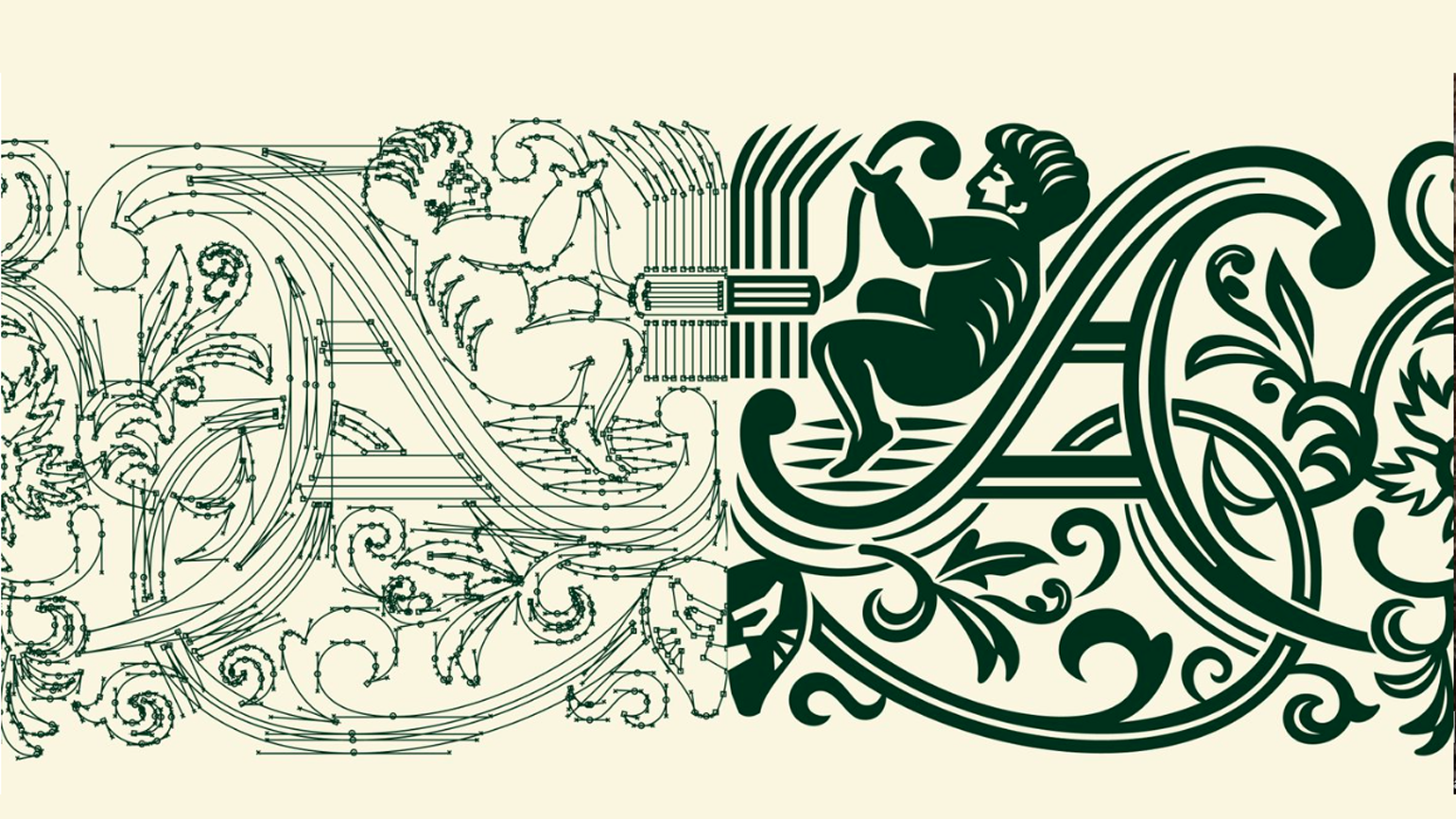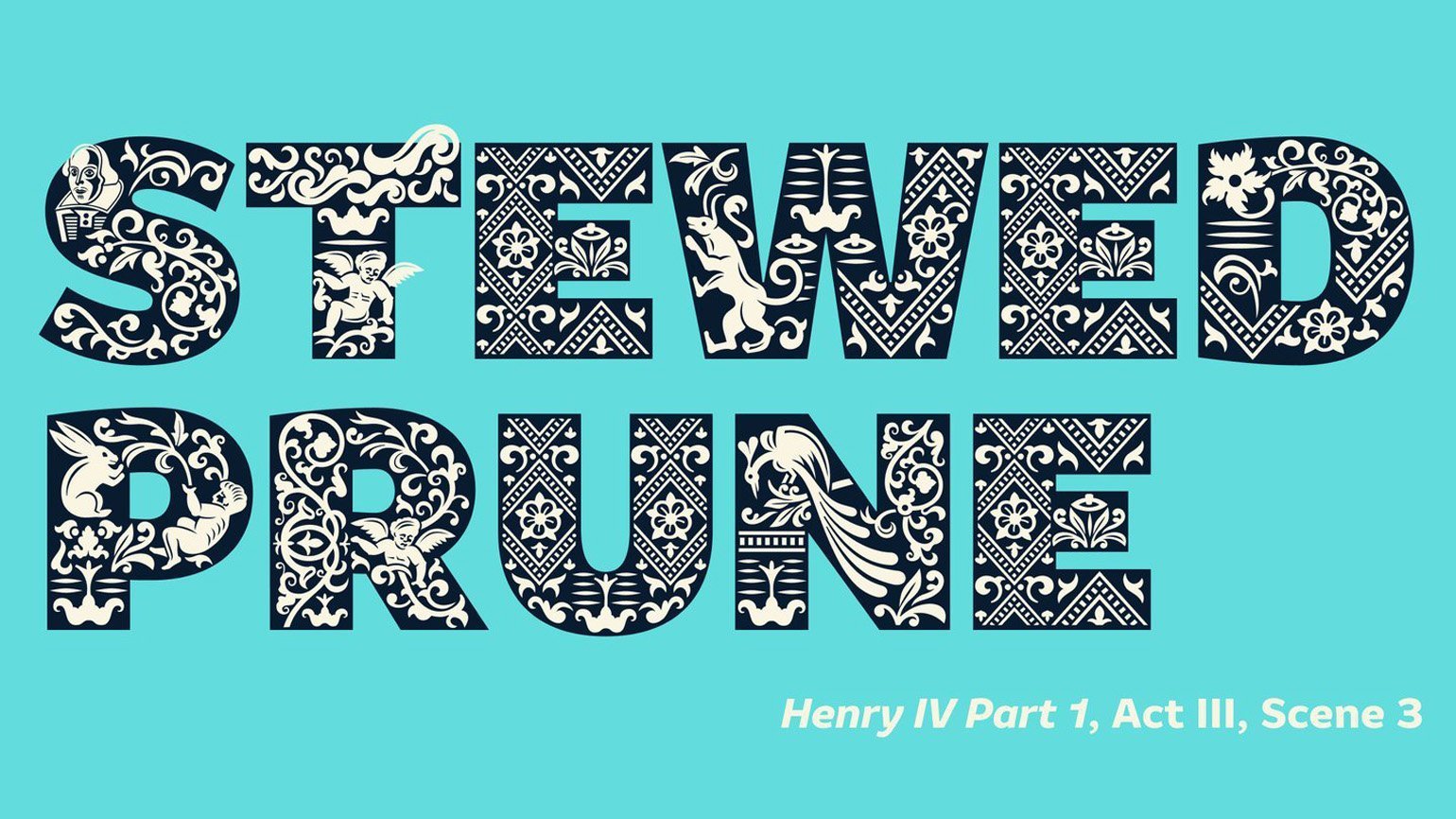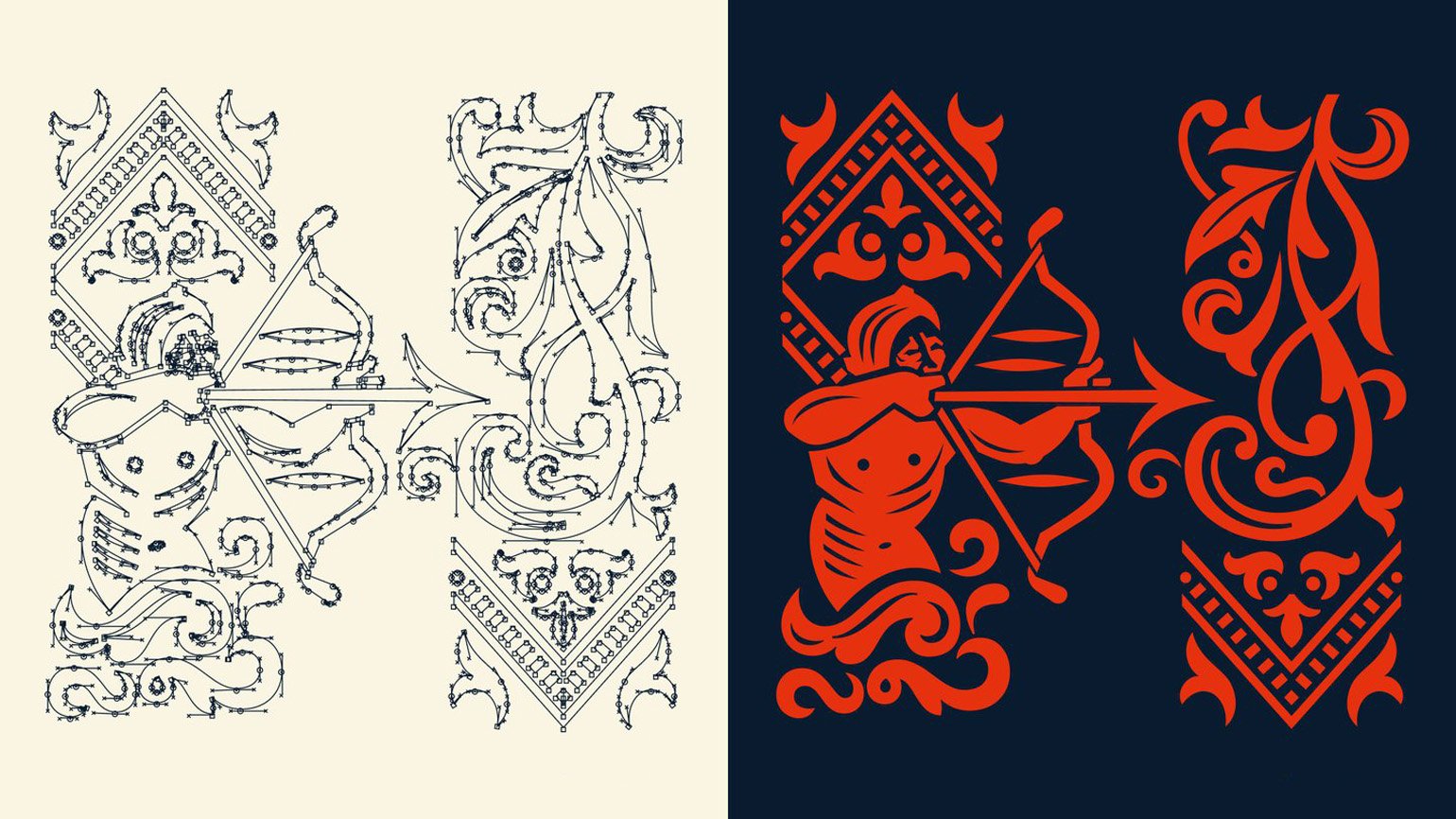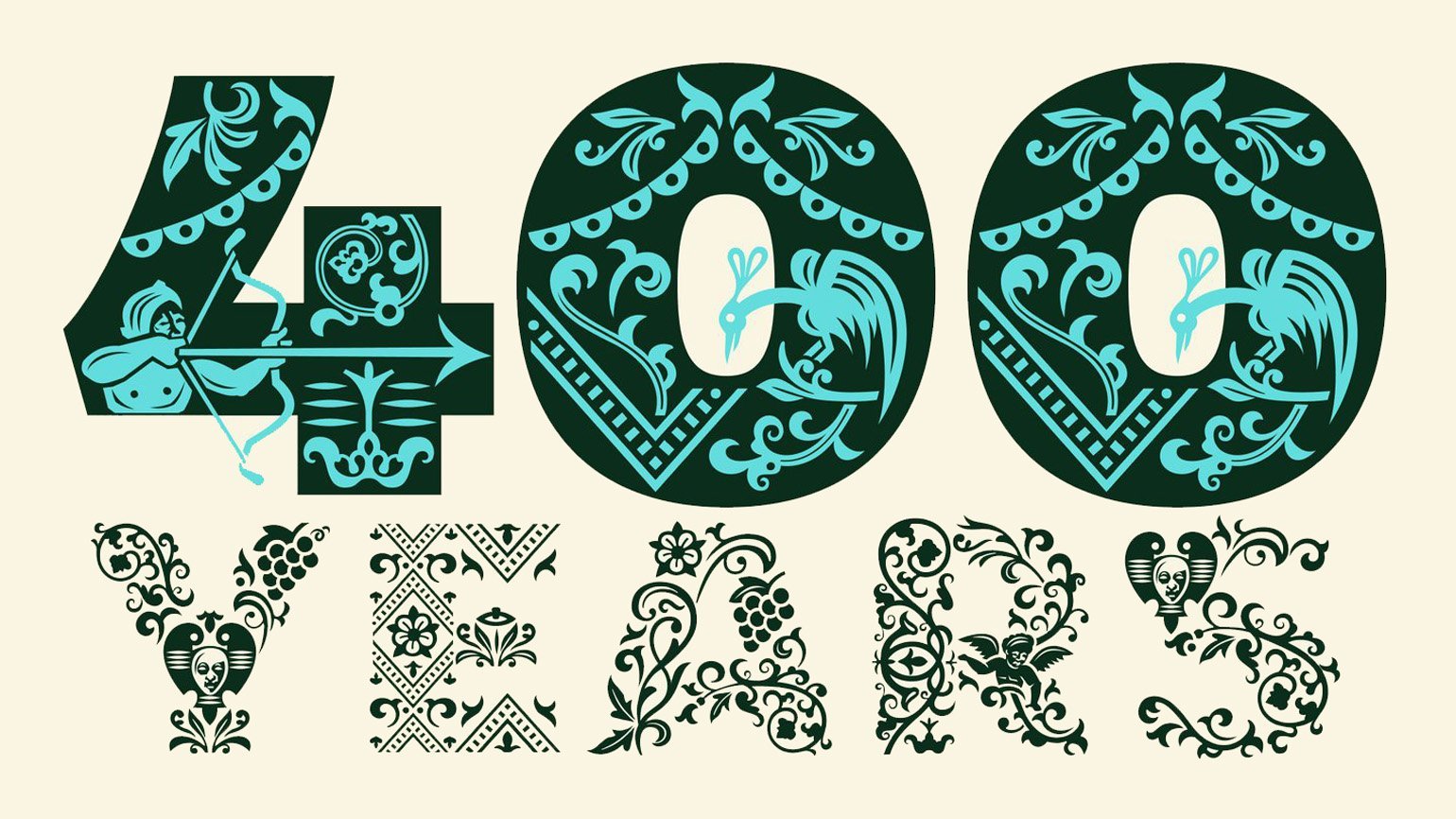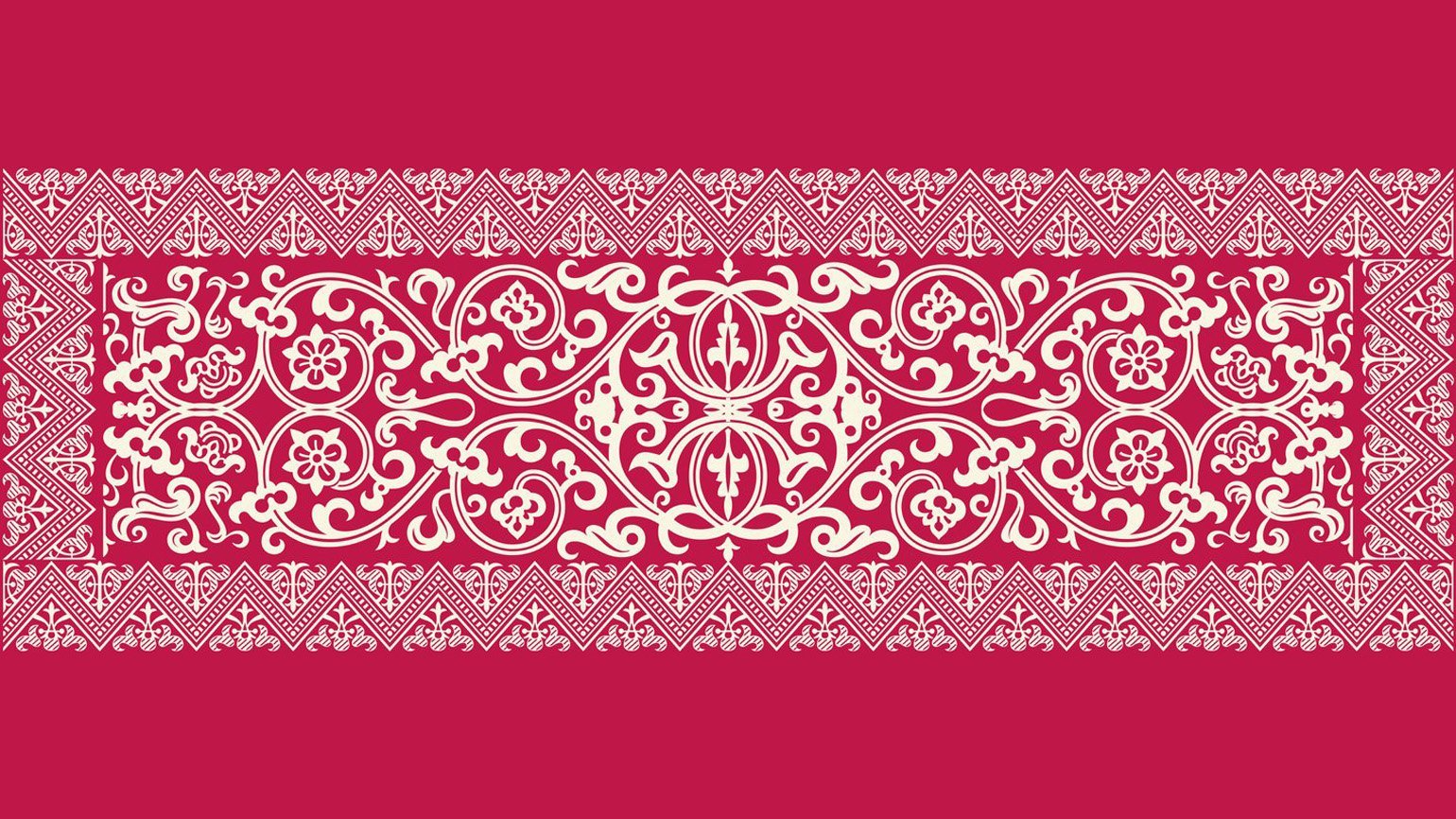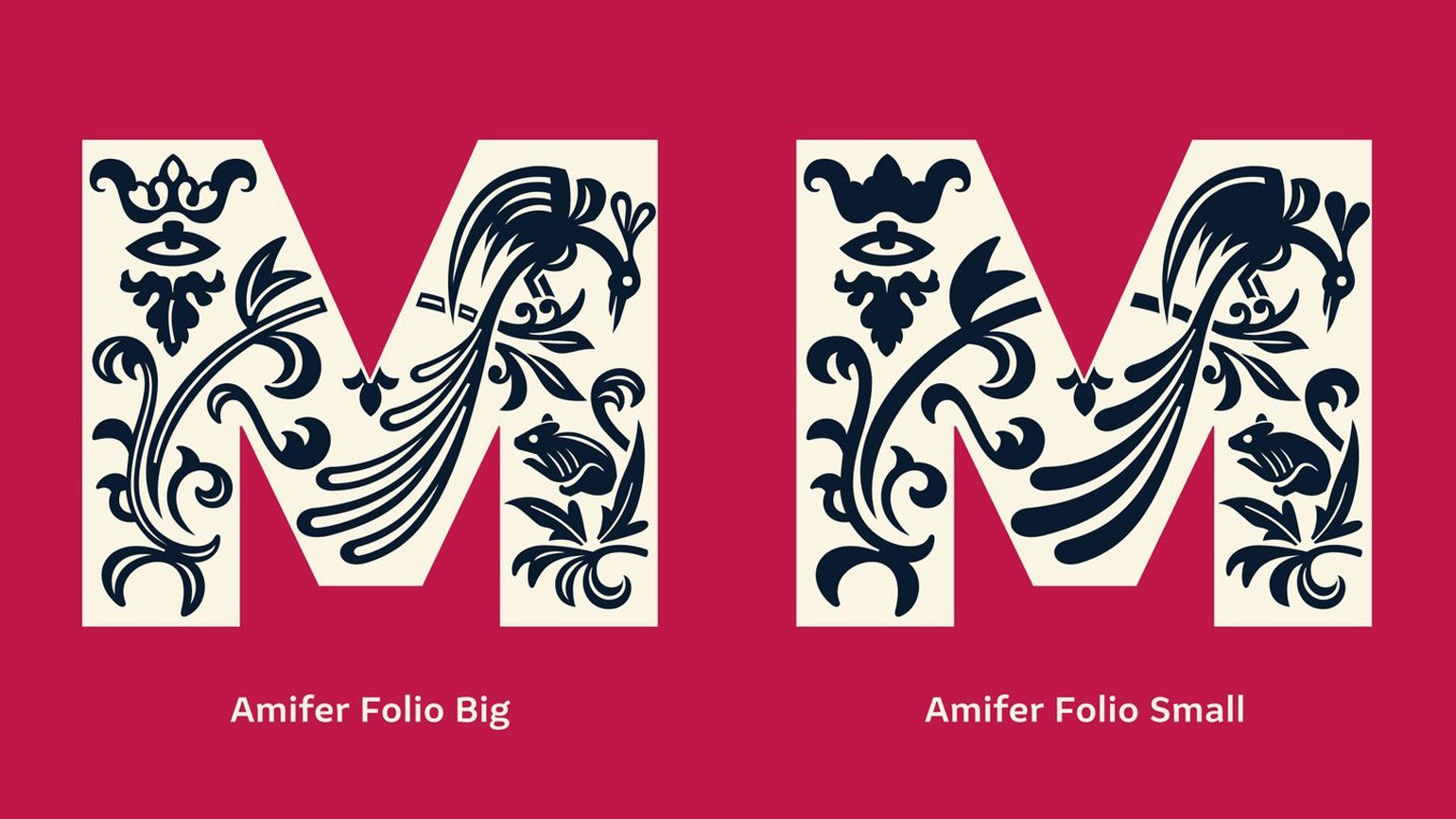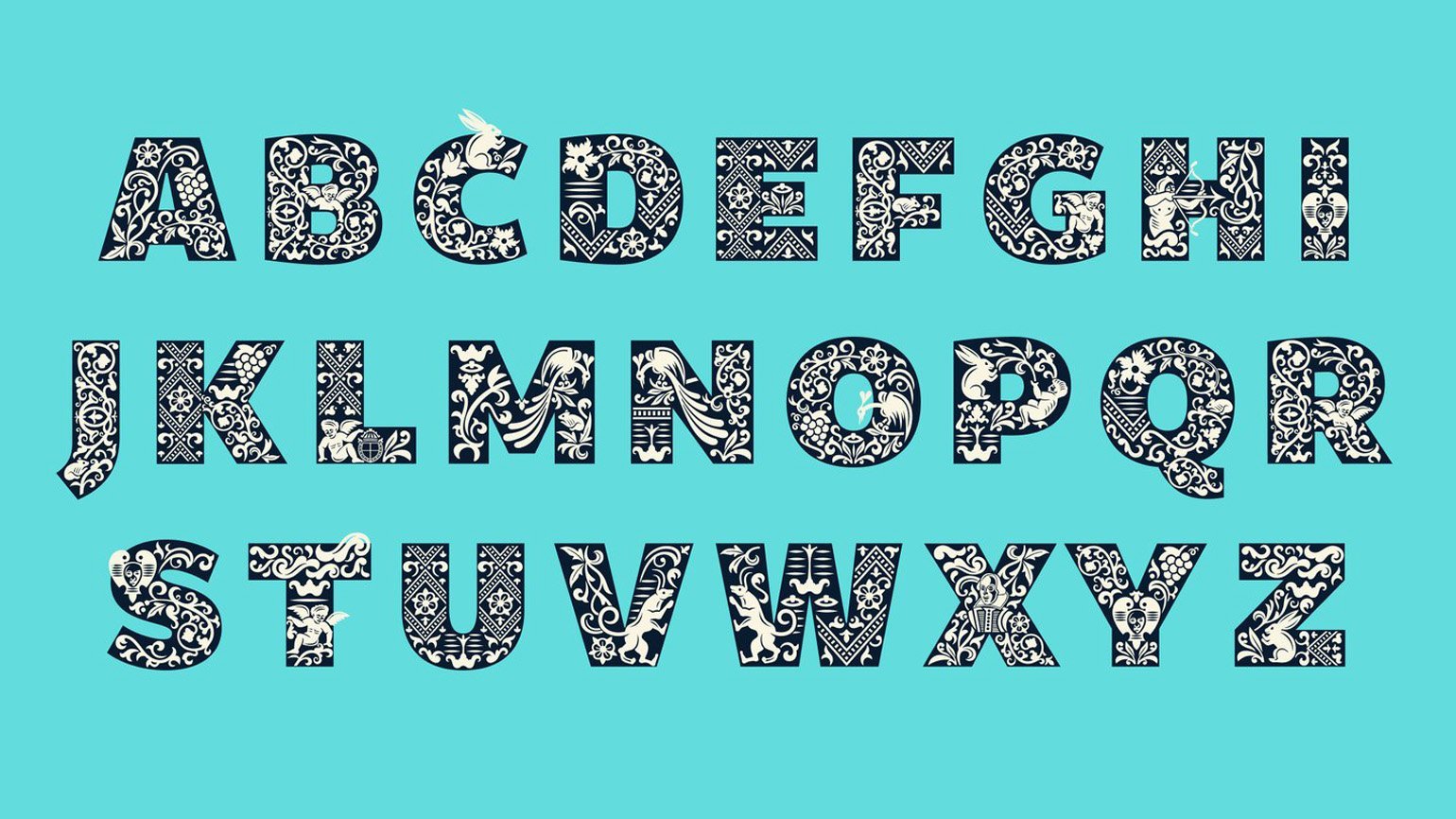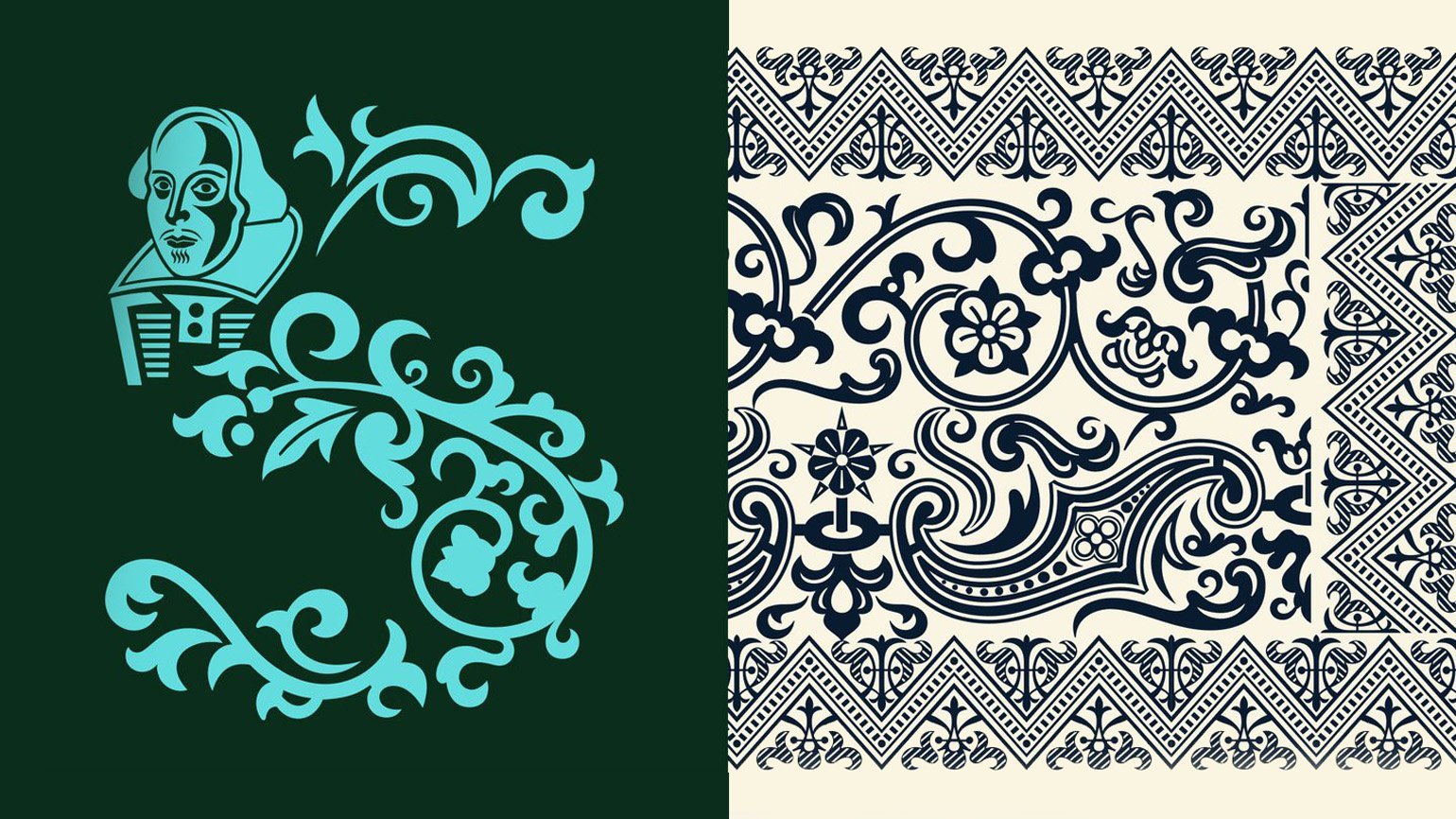
Театр Shakespeare’s Globe представил шрифт, вдохновлённый ренессансными гравюрами
Amifer Folio разработала студия Typeland в честь 400-летия Первого фолио Шекспира.
Первое фолио Шекспира — это первое собрание сочинений поэта и драматурга, напечатанное спустя 7 лет после его смерти. Его опубликовали в 1623 году под заглавием: «Мистера Уильяма Шекспира комедии, хроники и трагедии. Напечатано с точных и подлинных текстов». В честь четырёхсотлетия книги театр Shakespeare’s Globe совместно со студией Typeland разработал шрифт на основе гравюр на дереве из него.
Шрифт и графика Amifer Folio
Лондонская студия шрифтового дизайна уже работала с Globe, поскольку в предыдущих театральных сезонах учреждение использовало шрифт Amifer. По словам соучредителя Typeland Алессии Маццареллы, арт-директор The Globe Ирен Омодео Зорини обратилась к Typeland с идеей «добавить иллюстрированные буквицы» в Amifer для летней кампании 2023 года.
Шрифт и графика Amifer Folio
Орнаментированные буквы — это распространённый приём в средневековой и ренессансной типографике, позволяющий разделять главы и абзацы. Typeland должна была интерпретировать буквы из фолио, осовременив их и привязав к теме природы, — она будет центральной в новом театральном сезоне. Гравюры на дереве служат идеальным напоминанием о хрупкости и красоте мира природы — не только визуально, но и из-за их редкости, поскольку они существуют менее чем в 200 оставшихся экземплярах фолио», — поясняется в пресс-релизе.
Шрифт и графика Amifer Folio
Соучредитель Typeland Вайбхав Сингх говорит, что самой большой проблемой была разработка иллюстративных деталей, которые могли бы хорошо работать в разных масштабах. Экспериментируя с уровнем сложности буквицы, Typeland пришла к идее создания двух разных шрифтов — Amifer Folio Big и Amifer Folio Small, — которые можно использовать в комбинации для контроля желаемого уровня детализации.
Шрифт и графика Amifer Folio
Другой проблемой был перевод гравюр на дереве в цифровой формат. «Ксилографии отпечатали с расчётом на то, чтобы с ними можно было работать только в определённом масштабе, и нарисовать их так, чтобы их форма работала в цифровом шрифте при использовании разных размеров точек, может быть непросто», — говорит Сингх.
Шрифт и графика Amifer Folio
В каждом из вариантов шрифта проработан «особый набор персонажей» — от ангельских и демонических существ до горгулий, взятых из гравюр на дереве Первого фолио. На плакатах будут использовать яркие цвета, как и два года до этого.
Шрифт и графика Amifer Folio